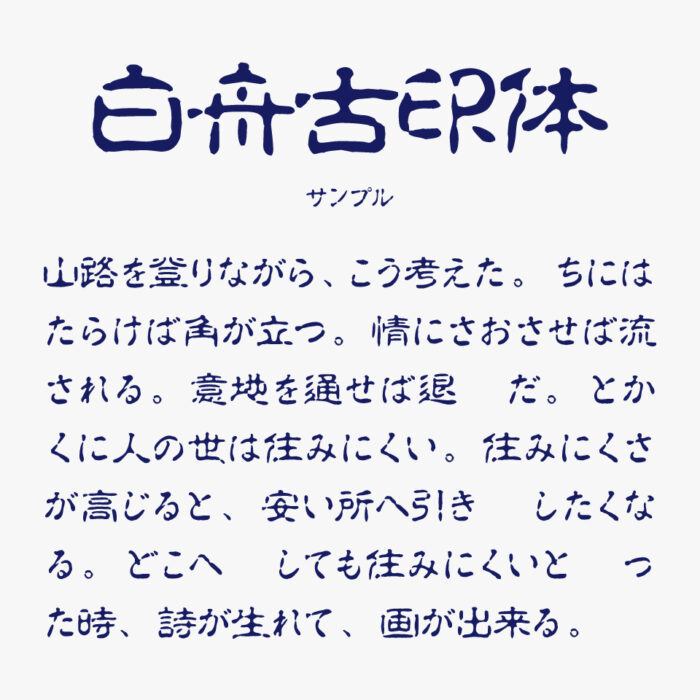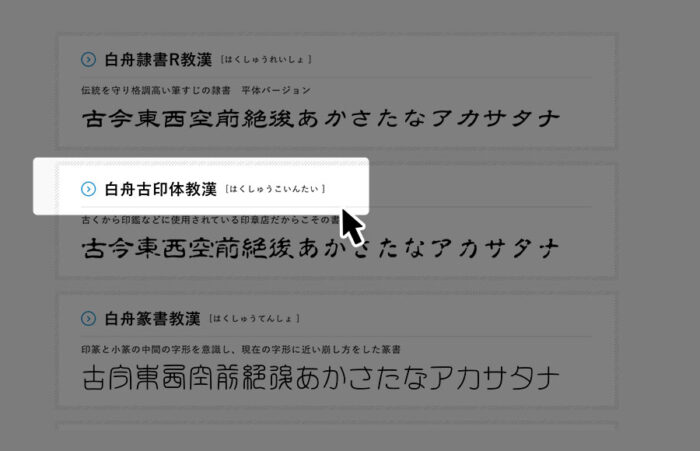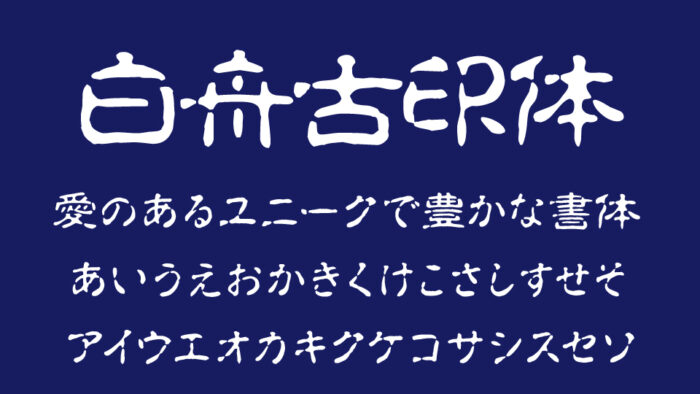
白舟古印体フォントは、筆で刻印したような骨太で渋みのある風合いが特徴的な古印体フォントです。
古印体(こいんたい)とは、古い印章(印鑑)や金石文(石や金属に刻まれた文字)などに見られる、太く丸みのある書体です。
白舟古印は、印鑑のようなかすれている質感があり、平体のようなフォルムをしていて、力強い印象のあるフォントです。